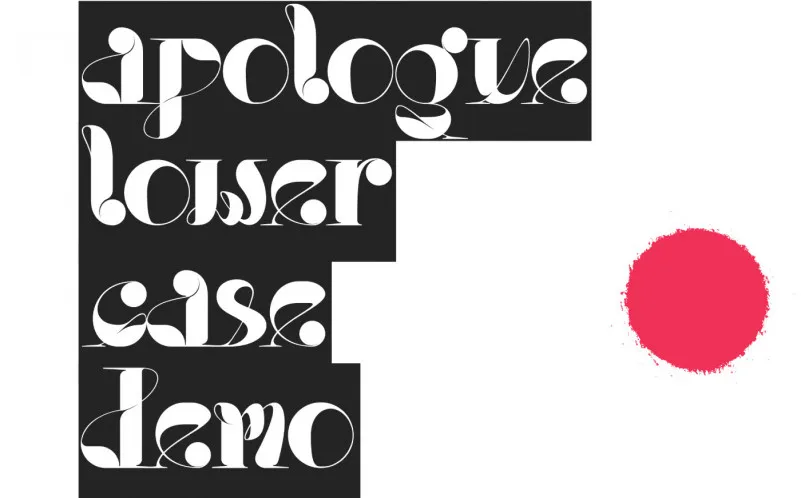
A Apologue Display Font oferece uma combinação única do 1970’s com arte Nouveau, perfeita para projetos digitais atuais e vintage ao mesmo tempo. Esta fonte abertamente se destaca como um tipo de display capaz de trabalhar em várias aplicações, desde o branding até a publicidade customizada. Sua aparência elegante e peculiar combina elementos artísticos com um toque moderno, tornando-a uma escolha ótima para uso em marcas de identidade, designs de logotipos, embalagens de produtos, material promocional, materiais decorativos domésticos ou até mesmo na capa de um livro. Com sua ligação e pontuação incorporadas, o Apologue Display Font se destaca como uma opção versátil que pode ser usada em qualquer projeto design que você possa imaginar. Seja para criar uma camiseta customizada, decorar um papel com um convite especial ou até mesmo personalizar uma caneca, a Apologue Display font certamente encaixará perfeitamente em seu próximo projeto criativo.